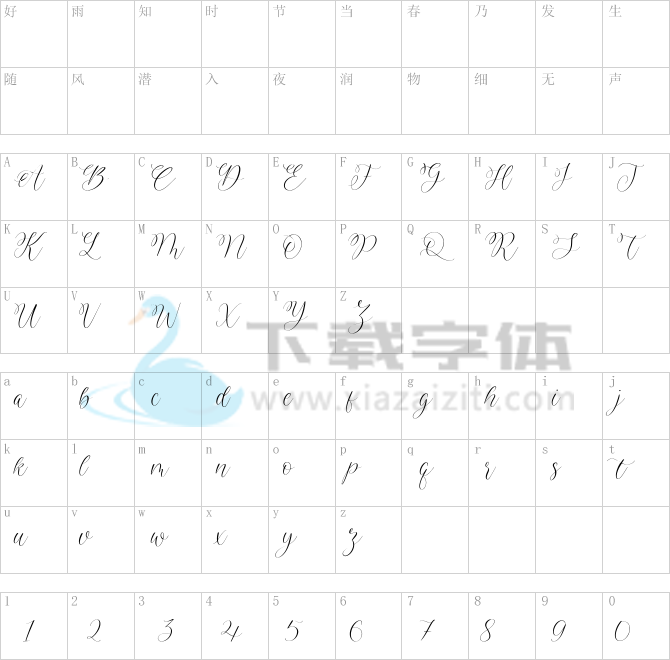
Avalien.ttf字体下载,这款字体结构工整、笔画清晰,兼顾美观与易读性,适用于标题、正文、海报、包装、LOGO 等多种场景。字形优雅稳定,风格百搭耐看,适配日常排版与创意设计,让文字呈现更舒适、更具质感。Avalien.ttf字体下载一笔一画,皆是细节,以均衡的比例、流畅的线条打造舒适视觉体验,字形端正大气,风格简约现代。无论是商业设计、品牌宣传还是日常排版,都能轻松驾驭,让文字更有格调与力量。Avalien.ttf字体下载字体下载。
• 字体名称:Avalien